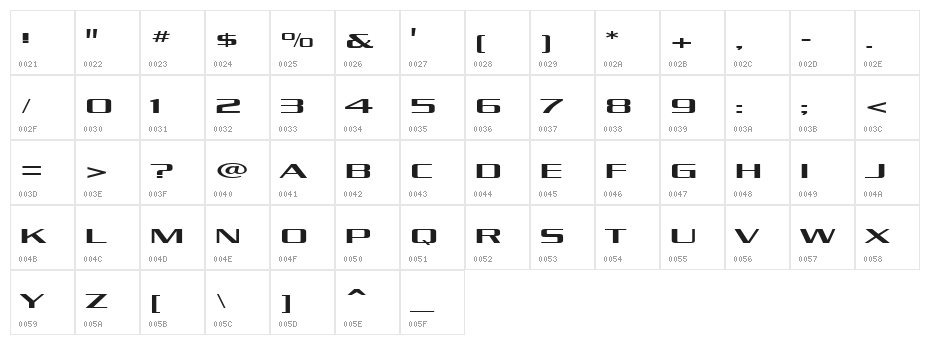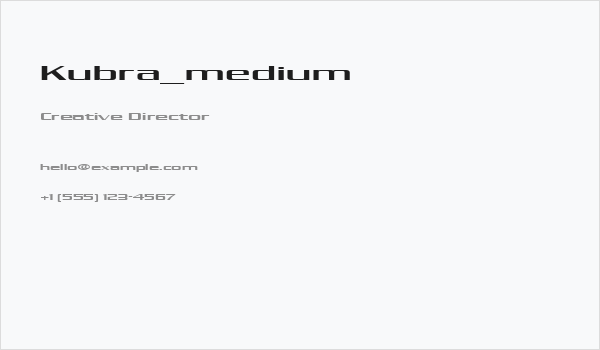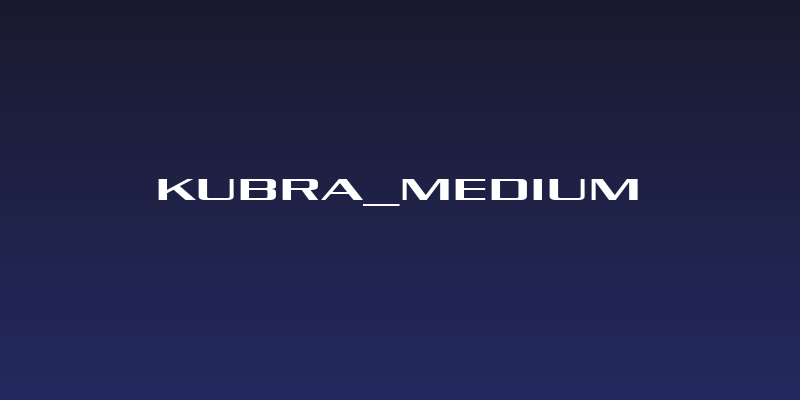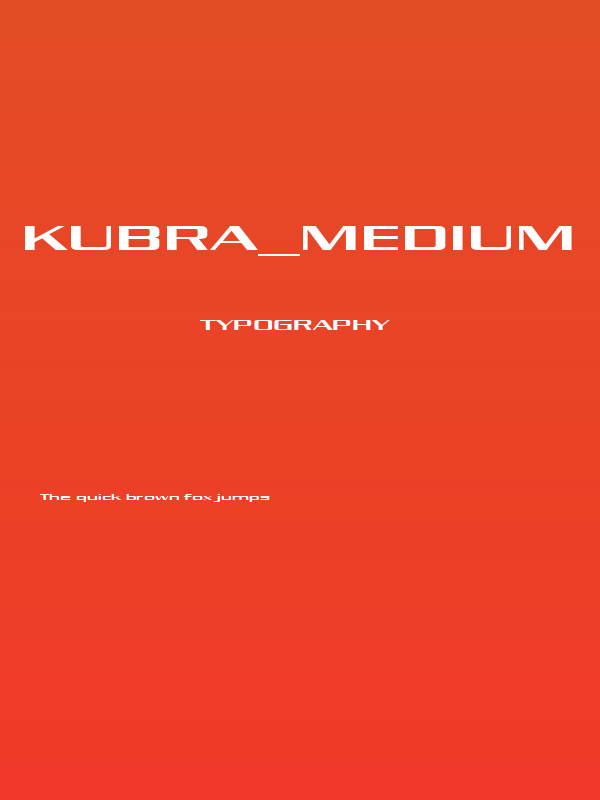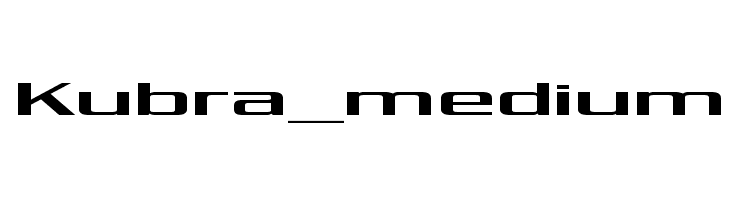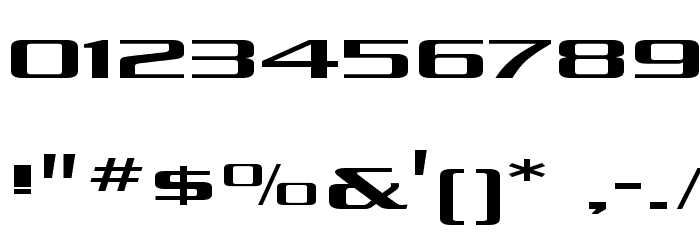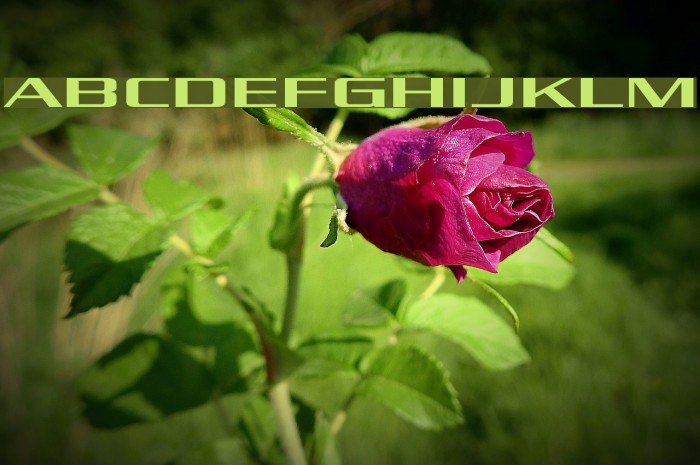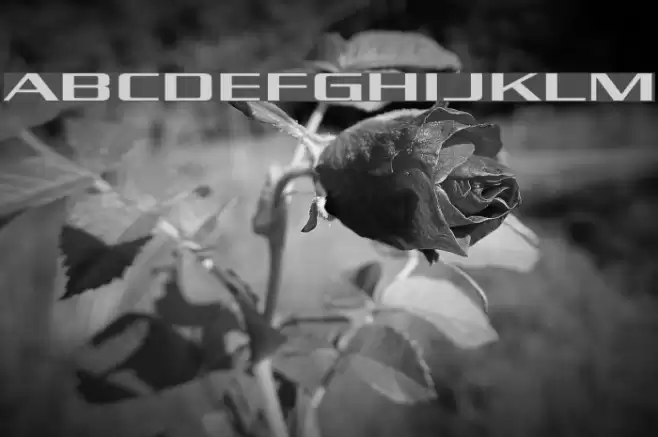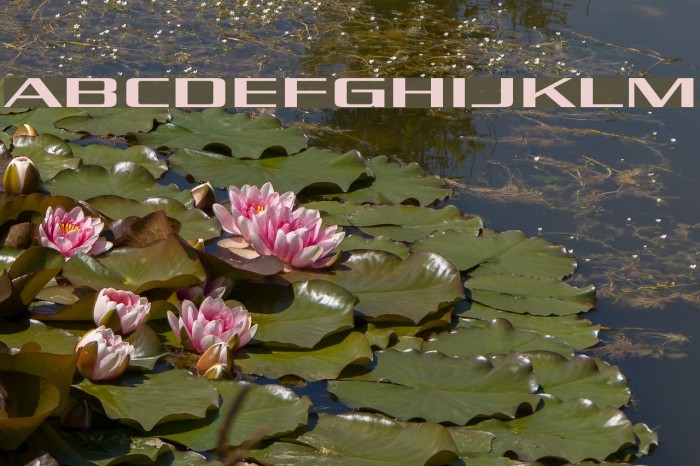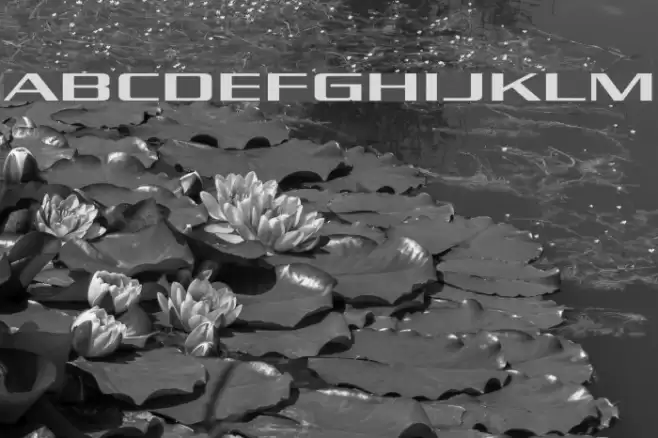
Kubra_medium Font
✎ Futuristic
| Anwendungsfall | Headlines, Logos, Branding |
| Vorgeschlagene Projekte | Ideal for branding, headlines, posters, and digital media where a strong visual impact is desired. |